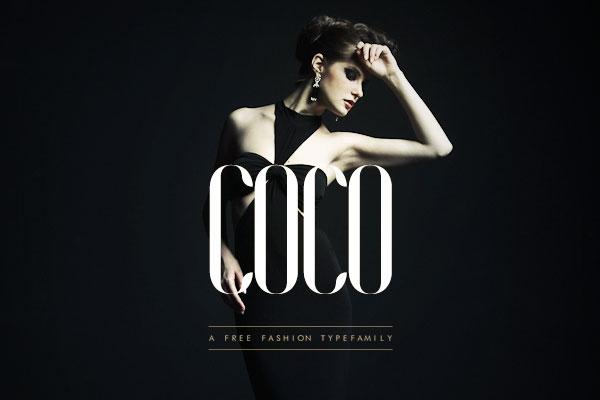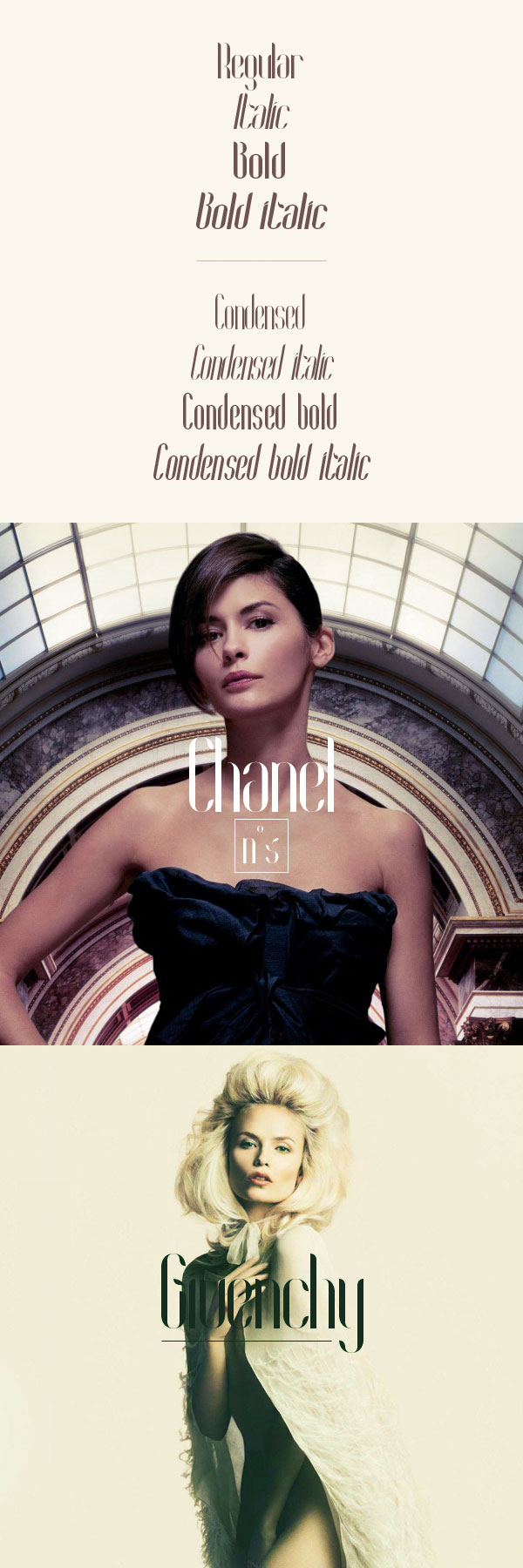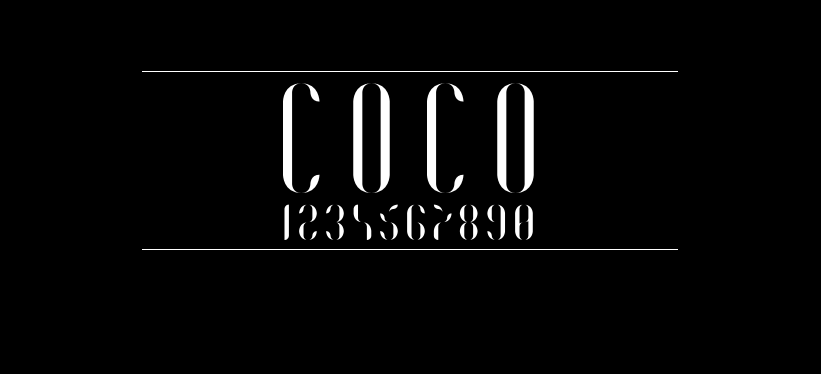
Coco
Coco字体是国外设计师Hendrick Rolandez于2012年创作的一款英文字体,虽然时间已经过去9年,现在已经是2021年了,但是以现在的眼光来看,COCO字体依然不失优雅,并富含神秘感。
Coco是sans-serif类型的字体家族,由8种字体组成,其中包括常规,斜体,粗体,粗体斜体,精简,精简斜体,精简粗体和精简粗体斜体,可用于多种类型的项目,从数字到打印。每种字体都有209多个字形,包括小写字母,大写字母,数字和特殊字形和标点符号。这个家庭适合所有想要强调时装项目的类型爱好者。因此,无论您是导演,设计师,摄影师还是模特,都可以自由使用,共享和创作令人惊叹的作品。